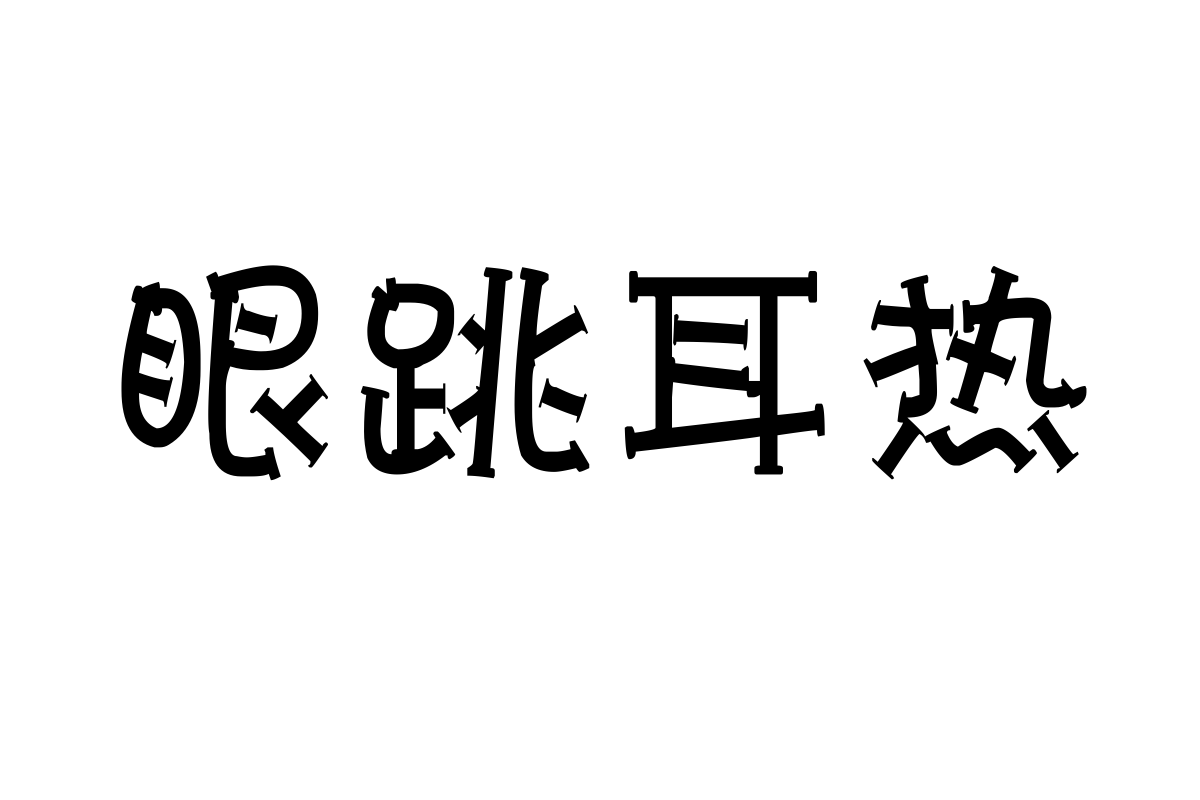
汉标工字体是一套由汉标公司推出的中文字体,它包含了多个不同的字型组合,适用于多种应用场景。这些字型的设计风格多样,既有传统的书法风格,也有现代简洁的风格,能够满足不同用户的个性化需求。
汉标工字体的特点包括:
1. 字形美观:每个字型都经过精心设计,字形优美,线条流畅,能够很好地表达汉字的美感。
2. 易读性强:字体结构清晰,笔画分明,使得阅读起来更加方便。
3. 适用范围广:无论是用于印刷品、广告、网站还是其他媒体,汉标工字体都能够适应各种场景的需求。
5. 可定制性强:汉标公司提供丰富的字库资源,用户可以根据自己的需求进行定制,打造出独特的字体效果。
总之,汉标工字体是一款功能强大、适用范围广泛的中文字体,能够满足各类用户在不同场合下对字体的需求。